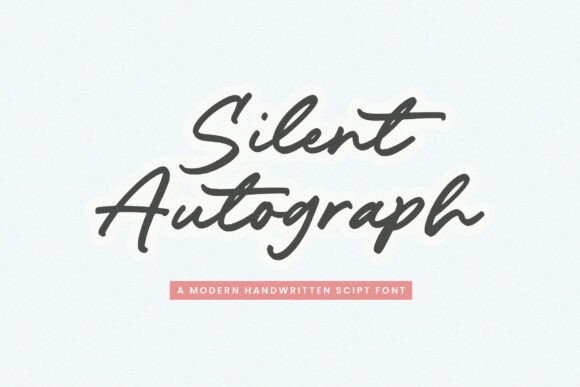
Silent Autograph
Silent Autographのような高品質の素材をお探しの場合、このプレミアムパッケージはクリエイティブなプロジェクトに素晴らしい選択です。
POD(オンデマンド印刷)製品、結婚式の招待状、またはソーシャルメディアのグラフィックを作成している場合でも、Silent Autographは理想的です。